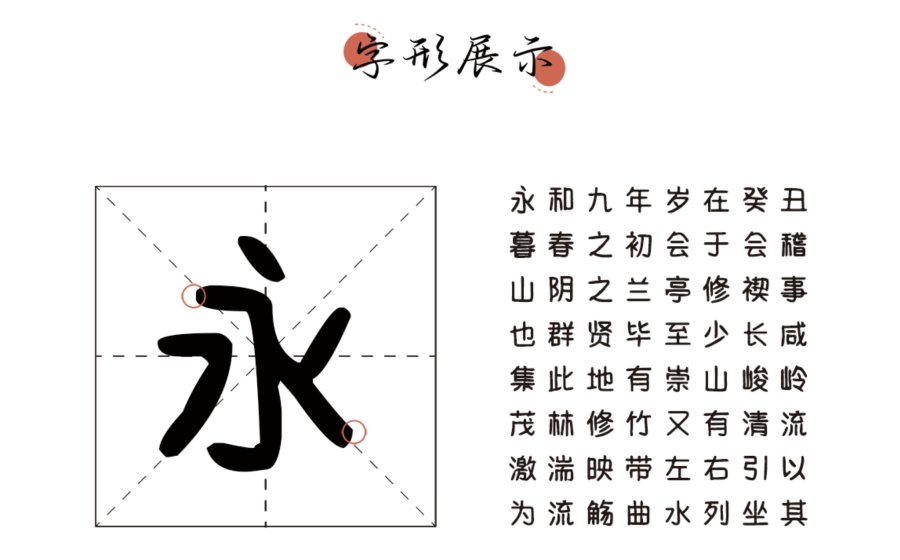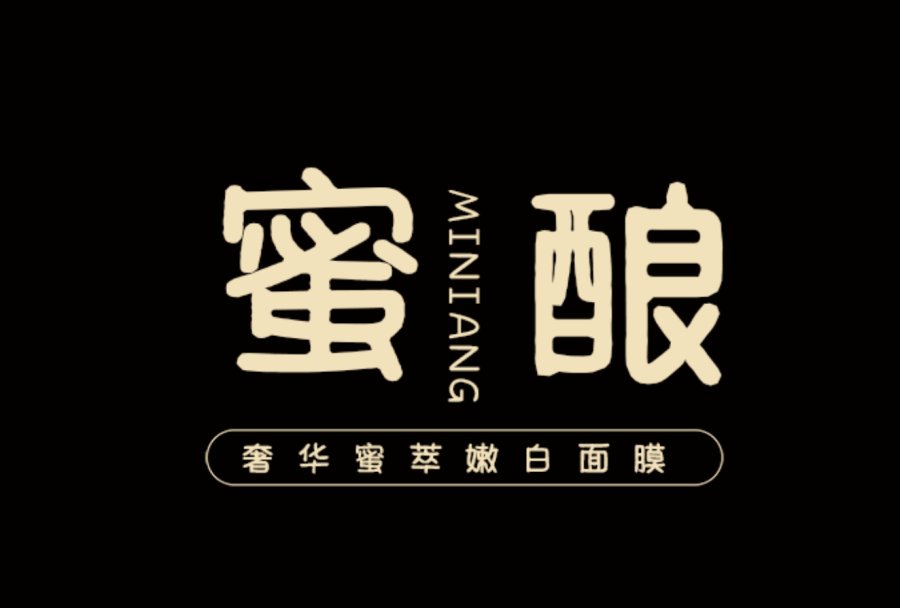
小熊冻冻奶字体是一款非常可爱的手写字体,其字体线条柔和而不失清晰,小熊冰淇淋造型的设计更是充满童趣,让人忍不住想一口咬下去。该字体风格比一般的字体更有特色,连贯字迹显得干练而不凌乱,清新简明,给人一种轻松愉悦的感觉。
小熊冻冻奶字体适用于多种场景,例如儿童相关的设计,比如儿童图书、儿童玩具、儿童服装等,都可以采用这种字体来表现童趣和可爱的特点。此外,在各种明信片、广告海报和文艺设计中,也可以用小熊冻冻奶字体来打造一种清新可爱的风格。甚至在一些小清新的手账、卡片、日记等文具设计中也非常适用。这种字体具有鲜明的特点,可以让设计更具吸引力和辨识度,赢得更多人的喜欢和青睐。